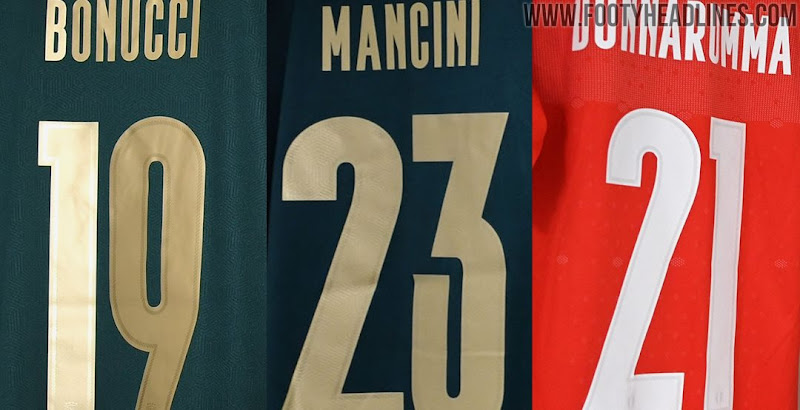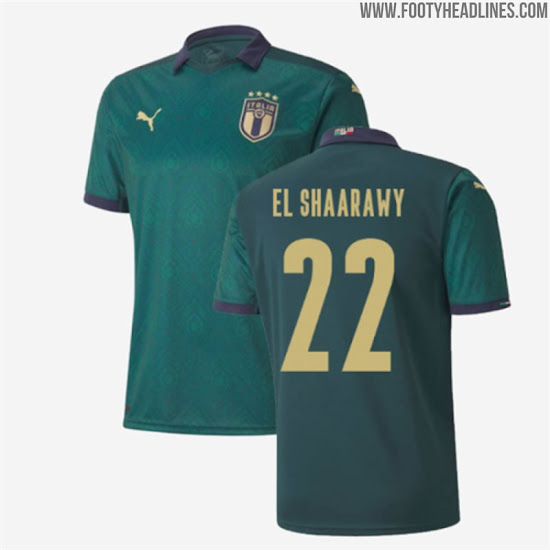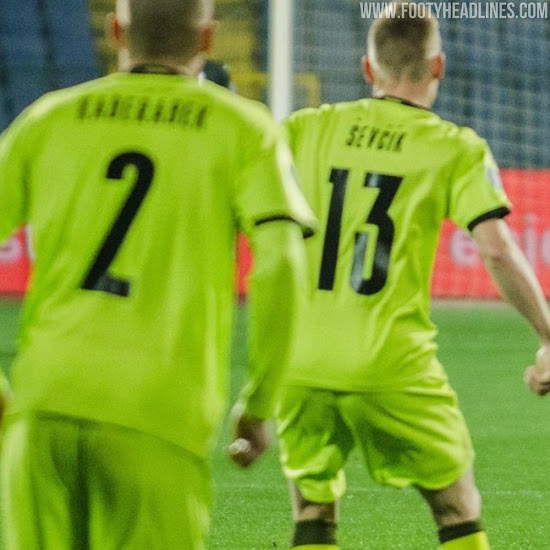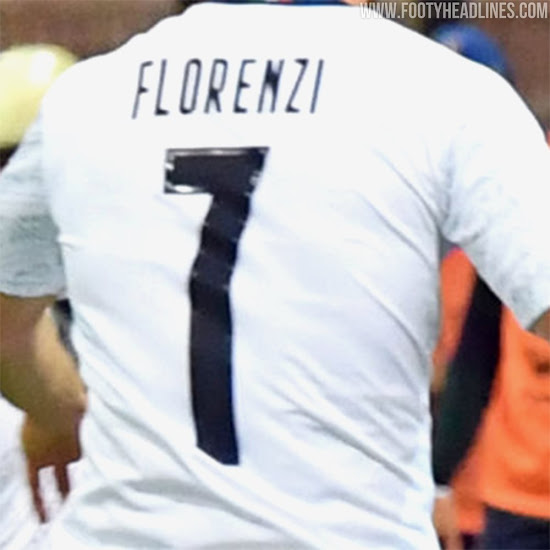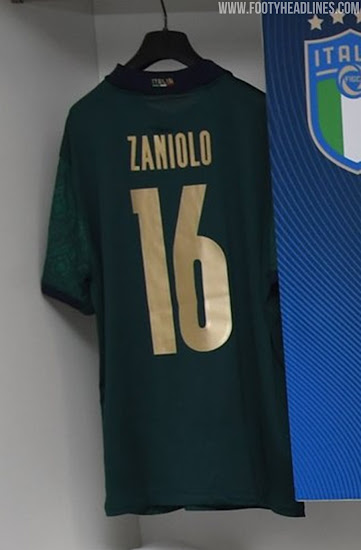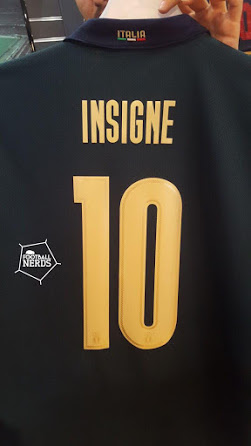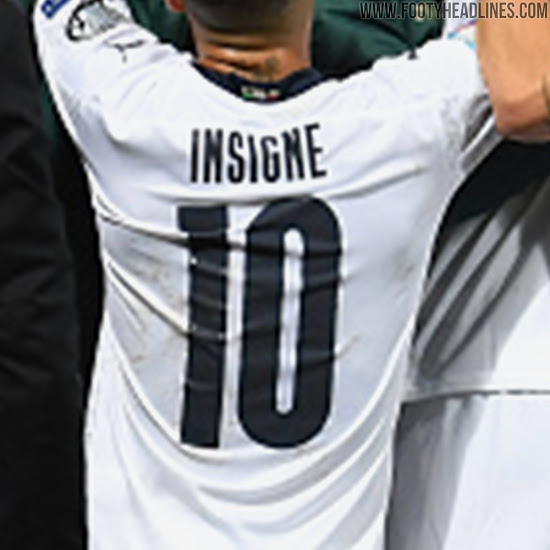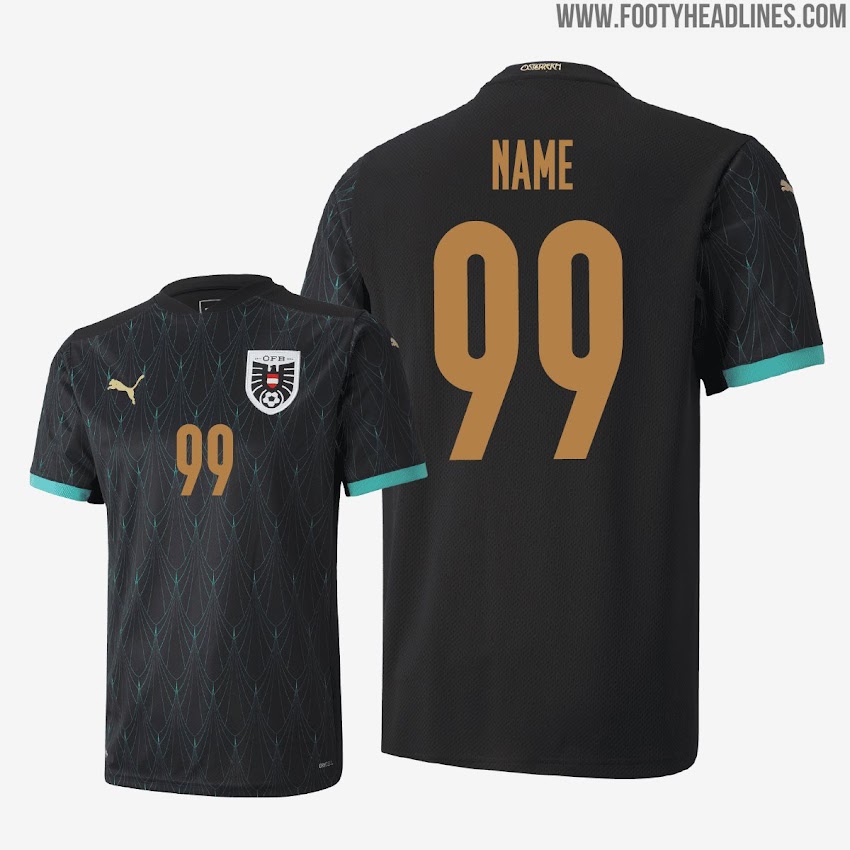
Universelle Puma EM 2020 Trikot-Schriftart enthüllt - Wird von allen Teams außer der Schweiz verwendet
Heute haben wir über die seltsame Schweiz EM 2020 Trikot-Schriftart berichtet. Die Schweiz ist jedoch das einzige Team, das eine "Standard-Schriftart" trägt - Puma hat eine eigene Schrift entwickelt, die von allen anderen Nationalmannschaften außer der Schweiz verwendet wird.
Tatsächlich wurde zunächst angenommen, dass Puma maßgeschneiderte Schriftarten für ihre Teams entwickeln würde. Tatsächlich haben wir bereits einen Blick auf die PUMA EM 2020 Schriftart geworfen, als die Marke ihr Italien 2019-2020 Ausweichtrikot veröffentlichte.
Puma EM 2020 Trikot-Schriftart
Die Puma EM 2020 Schrift für ihre Trikots zeichnet sich durch einen außergewöhnlichen Stil aus. Jede Zahl und jeder Buchstabe steht für sich, was jeden Namen sehr interessant macht.
Das einzige benutzerdefinierte Element für jede Nation ist, dass die Zahl auf der Rückseite mit dem Wappen des Verbands am unteren Ende versehen ist.
Es ist noch nicht bekannt, ob Puma die Schrift auch für einige der 2020-2021 Vereinstrikots verwenden wird.